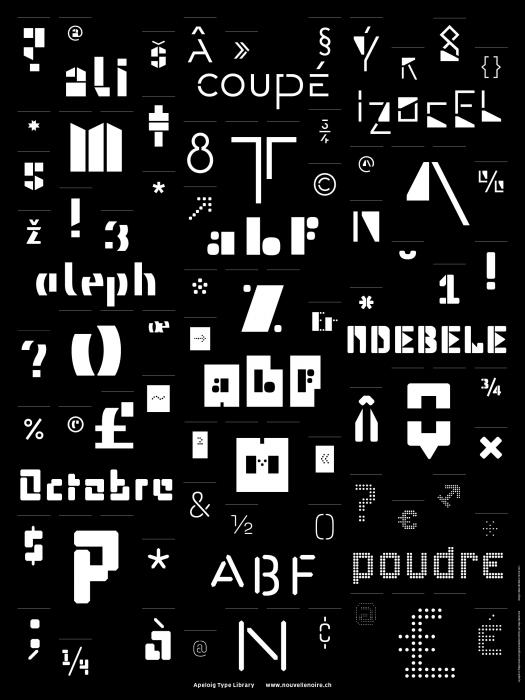
Apeloig Type Library
Nouvelle Noire haben heute zehn Schriften des französischen Grafikdesigners Philippe Apeloig als Apeloig Type Library veröffentlicht:
Originating from orders of posters, book covers or corporate and visual identities, those fonts came to life first as a few letters designed especially for the project. For Philippe Apeloig, Nouvelle Noire has undertaken the development of typefaces from those several existing letters. In the past two years, Nouvelle Noire developed the designs into ten full working fonts.
Was haltet ihr von dieser Veröffentlichung? Viele seiner Schriftentwürfe empfinde ich als äußerst eigenständig. Ihre volle Wirkung entfalten Apeloigs Schriften vor allem in seinen grafischen Arbeiten. Das ist aber zugleich auch der Grund, weshalb ich sie bei eigenen Arbeiten höchstwahrscheinlich nicht einsetzen würde. Der Duktus und die Formensprache seiner Schriften sind für meinen Geschmack zu sehr mit Apeloigs Arbeiten verbunden. Zumindest hätte ich ein komisches Gefühl dabei, die Schriften für einen Logoentwurf o. Ä. zu verwenden. Wie geht es euch dabei?
Nur das Bild betrachtend (nicht die Links):
Das sieht konzeptionell und handwerklich alles gut aus – was ja grade bei solchen markanten Schriftexperimenten viel schwieriger ist als oft naiverweise angenommen.
Aber wie du sagst: solche Schriften leben von einer initialen Inszenierung (oft bestehend aus der Arbeit, für die sie ursprünglich entstanden sind), In einer Standard-Schriftprobe entfalten sie auch ihre Wirkung nicht, sie müssen "vearbeitet" werden bevor sie funktionieren, sind also eher grafische Elemente als Schriften in klassischem Sinne.
Sie einfach nochmal so einzusetzen wie im ursprünglichen Entwurf ist dann an der Grenze zwischen Schrifteinsatz und Design-"Übernahme". Andererseits finden sich auch immer wieder ganz überraschende Einsatzzwecke für Schriften, die man selbst längst in eine grafische Schublade gesteckt hat und aus der man sie gedanklich nicht mehr raus bringt ... insofern besteht auch hier Hoffnung :)